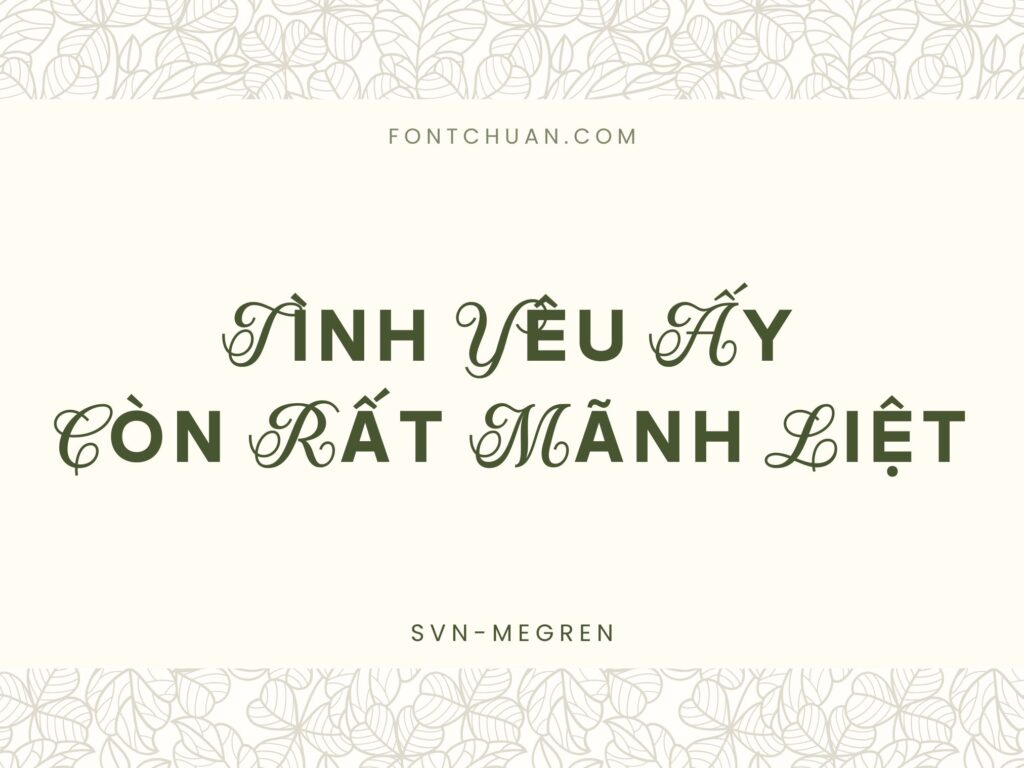
Font SVN Megren Việt Hóa
Tác giả Font: Zarma Type Foundry
Font SVN Megren là phiên bản Việt hóa của kiểu chữ Megren, được thực hiện bởi STYLEno.1 Fonts. Megren là một kiểu chữ hiển thị thử nghiệm, kết hợp độc đáo giữa các yếu tố của sans-serif hiện đại và script copperplate cổ điển. Thiết kế của font mang đến cảm giác mới mẻ, thời thượng và có phần hoài niệm, với chữ hoa được vẽ theo phong cách copperplate mảnh mai và chữ thường đơn giản, gọn gàng. Font bao gồm đầy đủ chữ cái, chữ số và dấu câu, đồng thời hỗ trợ đa ngôn ngữ. Kiểu chữ này rất linh hoạt và phù hợp trong nhiều dự án thiết kế đòi hỏi sự cá tính và sang trọng.
SVN Megren phù hợp để sử dụng trong các thiết kế như tiêu đề tạp chí, nhãn hiệu sản phẩm, poster sự kiện, bao bì mỹ phẩm hoặc các ấn phẩm truyền thông. Các ngành nghề như quảng cáo, giáo dục và công nghệ có thể tận dụng font này để tạo dấu ấn riêng biệt. Bên cạnh đó, font cũng đặc biệt phù hợp với các sự kiện như Tết, Giáng sinh, Valentine và các lễ hội trong năm.